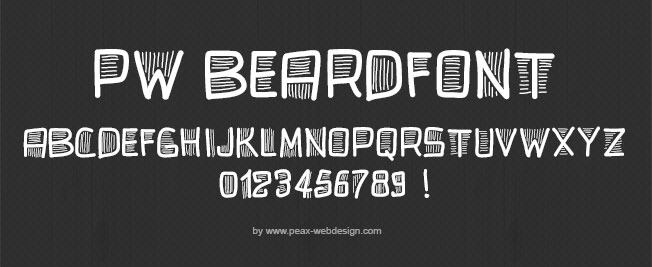
PW Beardfont, police manuscrite et barbue .ttf
Etant donné que la mode est à la barbe, voici une nouvelle typo qu'affectionneraient tout particulièrement Dusty Hill et Billy Gibbons de ZZ Top !
Des remplissages verticaux par-ci et par-là, une forme légèrement rectangulaire, quoi dire de plus ? Testez-là, elle saura stimuler votre créativité... à défaut de votre pilosité!